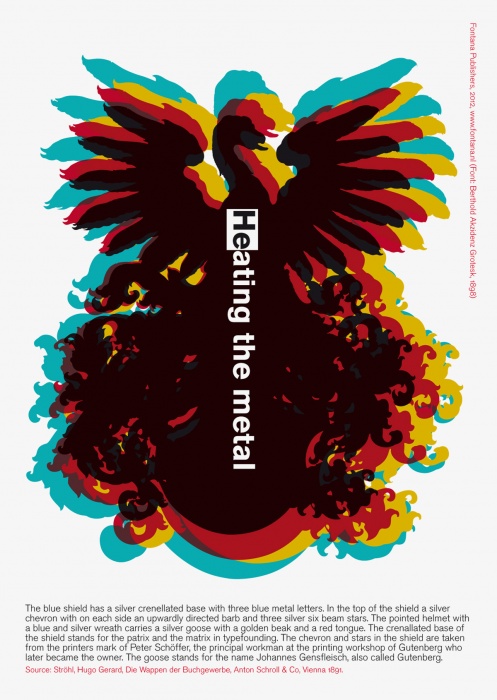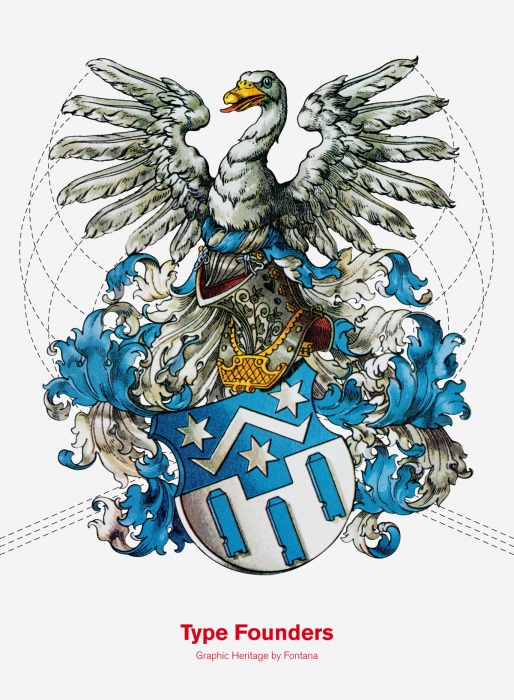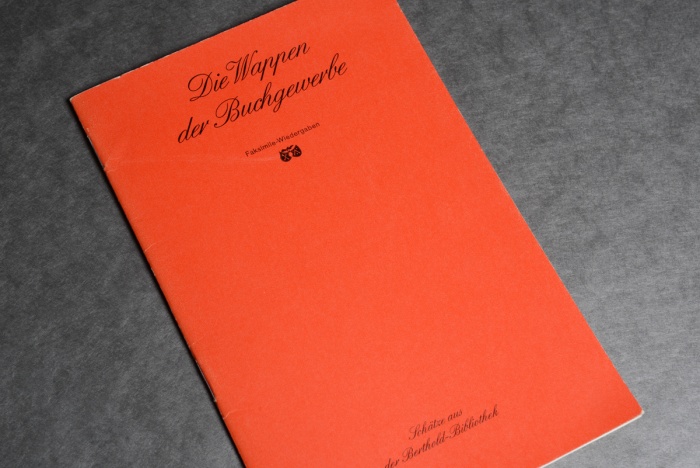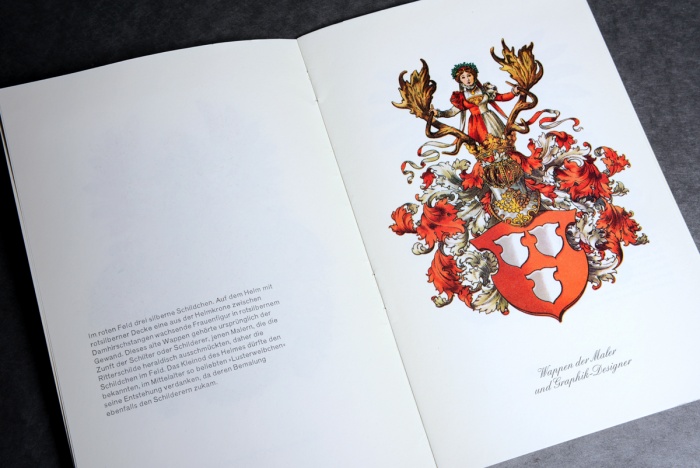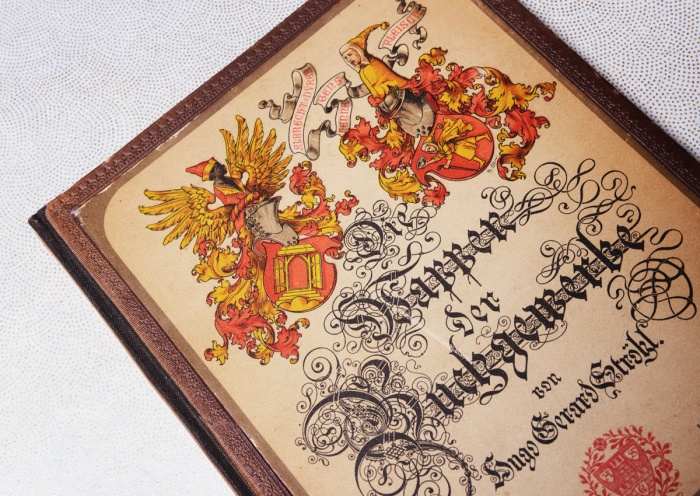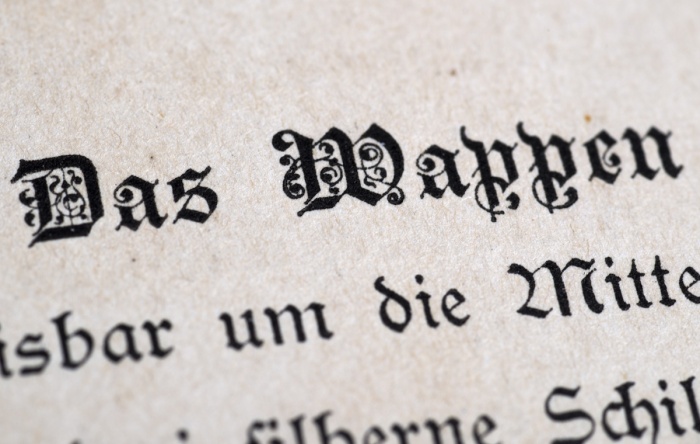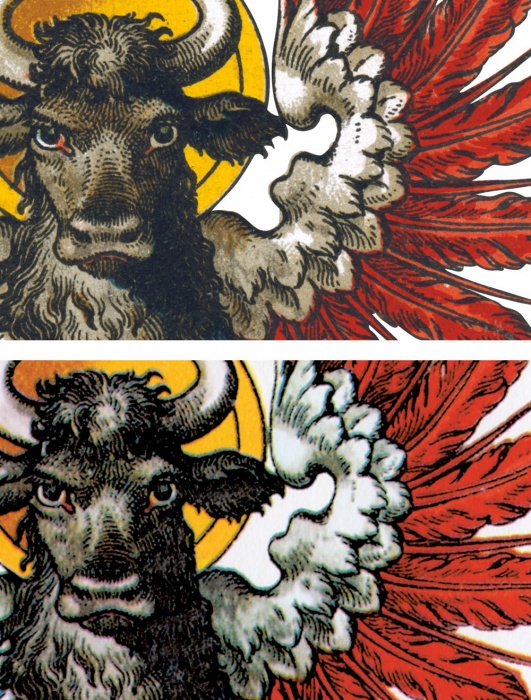
Die Wappen der Buchgewerbe – ein neues Projekt ...
In 2012 war ich wie immer auf der Suche nach Schriftproben und Ausgaben von Schriftgiessereien. So kaufte ich für 5 Euro unterstehendes Büchlein. Es ist eine ‘Faksimile-Wiedergabe’ von ‘Die Wappen der Buchgewerbe’ von Hugo Gerard Ströhl in der Reihe ‘Schätze aus der Berthold-Bibliothek’. Das originale Buch stammt aus 1891 und diese Berthold Ausgabe ist Weihnachten 1970 verschenkt worden an Kunden von Berthold. Die verwendete Schriften sind Englische Schreibschrift in Diatype Fotosatz und Akzidenz Grotesk mager als Handsatz. Auf der Vorderseite sieht mann auch die erstbekannte Druckermarke von Fust und Schöffer, zwei Wappen hängend an einen Ast, aus 1457. Im inneren 7 Wappen wovon eine zu sehen auf das zweite Bild. Es ist das Wappen der Maler, einer der ältest bekannte Wappen überhaupt. Berthold lässt sehen das rund 1970 der Beruf der Graphik-Designer immer wichtiger wurde und so wurde das Wappen der Maler auch das Wapper der Graphik-Designer in diese Ausgabe.
Viele Graphik Designer werden sich fragen was das soll mit diese Wappen. Meistens ist es nicht etwas was mann Heutzutage noch zur Hand nehmen würde anders als aus Nostalgie. Aber in unterstehendes Bild zeigt sich das dies sich gut in diese Zeit transformieren lässt. Dies ist eine Postkarte die Fashion Designer Paul Smith mir schickte. Die Karte ist aufgebaut aus drei Schichten Papier. In der Mitte ein dickes dunkelblaues Papier und vorne und Hinten dünneres weisses Papier die laminiert sind. Hier ist nichts gedruckt sondern nur gelasert damit das blaue Papier das Bild formt. Auch die Typografie passt meiner Hinsicht nach sehr gut. Und das Motto sollte jeder Designer haben ...
Obwohl die Wappen in das Büchlein von Berthold sehr altmodisch erscheinen hatten wir schon vorher alte Zeichnungen verarbeitet in Postkarten die wir als Mitgabe mit unsere Niederländische Letterfontäne Bücher mitgegeben hatten (Siehe die Karten mit Cartouches bei http://www.typografie.info/3/topic/28501-excoffons-calypso-pf-als-freier-download/page-2). Weil nach 1.000 Bücher die Cartouche-Karten vergeben waren wollten wir neue haben. Dann haben wir diese gemacht. Ein Vorbild von Vorder- und Rückseite der Karte von die Schriftgießer. Weil die Akzidenz Grotesk (1898) nur ein par Jahre später vorgestellt wurde fanden wir das ein schöner Kontrast mit die Arbeit von Ströhl aus 1891. Die alte Welt von vor 1900 mit die Wappen als erste „Corporate Indentities” und der neue typographischer Standard von der AG für das zwanzigste Jahrhundert.
Aber wir waren immer noch nicht zufrieden mit die scans aus das Berthold Büchlein. Die Bilder waren in 1970 gerastert und mit ‘descreening’ bei das Scannen wird das Bild Unscharf gemacht und dann wieder geschärft (Unsharp Masking). Detail geht dann verloren beim Rasteren für Druck und dann auch noch bei das Einscannen und Descreenen. Also wir suchten weiter um ein Original zu bekommen und fanden ein Buch aus dem Nachlass von Daniel de Bruin, einen Heraldiker der 2010 gestorben war. Auf den Umschalg links das Wappen von Dürer und rechts das Wappen von Henne Gensfleisch (Gutenberg): ‘... dießer beiden Größen auf graphischem Gebiete.’ Und natürlich eine herrliche Schrift für den Namen des Buches ...
Altmodisch und Heute praktisch nicht mehr brauchbar. Aber wie schön kann Geschichte sein?
(Titel aus Ströhls Buch)
Wir hatten das Buch von Ströhl wie gesagt gekauft weil wir dachten das die Qualitåt der Wappen besser sein würde. Und das war auch so. Das Original hat viel mehr Detail und die Farben sind auch nicht so Flach wie de Bilder aus die Berthold Ausgabe. Für einen neuen Satz Karten habe wir also die Bilder neu eingescannt. Hier unten ist der Unterschied zu sehen zwischen beide Bilder. Unten ist die Reproduktion aus die Berthold Ausgabe zu sehen mit mehr Kontrast aber weniger Detail und oben ist die aus das Buch von Ströhl aus 1891 zu sehen. Auch die Unschärfe unten ist deutlich zu sehen.
Übrigens ist das Detail im vorigen Beitrag von das Papiermacher Wappen. Der Ochsenkopf ist einer der ältesten Papierzeichen die bekannt sind. Bereits in Gutenbergs Bibeldrucken ist er nachzuweisen. Im Bild unten ist dieser Ochsenkopf in ein Wasserzeichen in Gutenbergs Bibel zu sehen. Gutenberg hat Papier verwendet von mehrere Papiermühlen weil er ziemlich viel Papier brauchte für seine Bibeldrucke. Das gezeigte Papier unten mit den Ochsenkopf ist aus Caselle, Italien.
Heute haben wir unsere neue Publikation ‘The Coats of Arms of the Book Trade’ bekommen. Wie gewohnt ein wenig ‘geeky’ und wahrscheinlich nur für Leute die genau wie uns etwas zu tief in ein Thema hereinsteigen (Nerds?). Leider nur in English weil die meiste Fans von unseren Publikationen English verstehen. Die Auflage ist beschränkt auf 250 Stück und sind numeriert und signiert.
Die Publikation ist nicht gross aber sehr aufwendig produziert. Der Umschlag is recycled Cairn Board aus England, bedruckt in zwei Farben Foliendruck. Das Band ist aus Japanisches Washi Yuzen papier, bedruckt in siebdruck mit ein geometrisches Muster in Gold, Das Büchlein von 16 Seiten ist auf Naturpapier gedruckt in Vier Farben mit vielen Vorbilder. Die 6 Karten in die Mappe sind auf Chromolux Pearl gedruckt. Alles is verpackt in Seiden Papier und Gebunden mit Finnisches Papierkordel (Waschbar bis 40°C????) und als kleines Schmuckstück eine gestanztes Kärtchen aus Duplex-Papier.